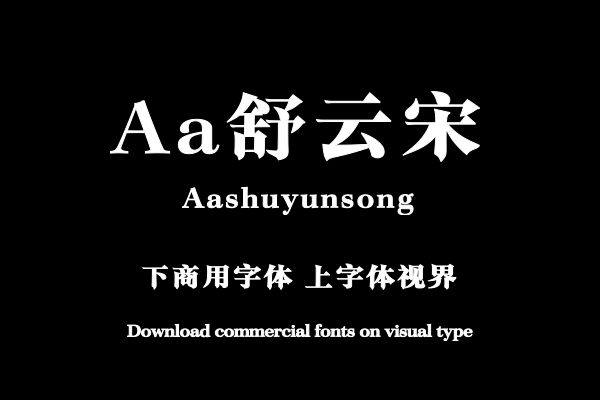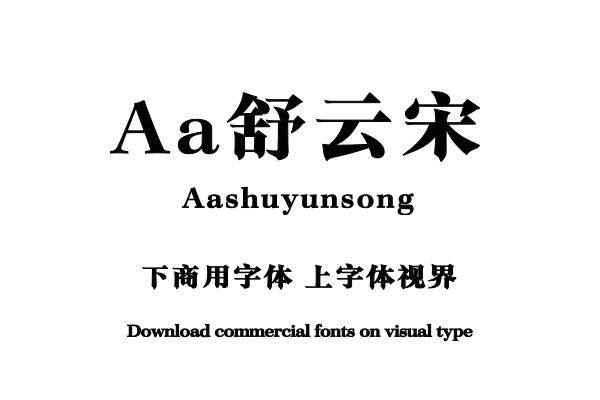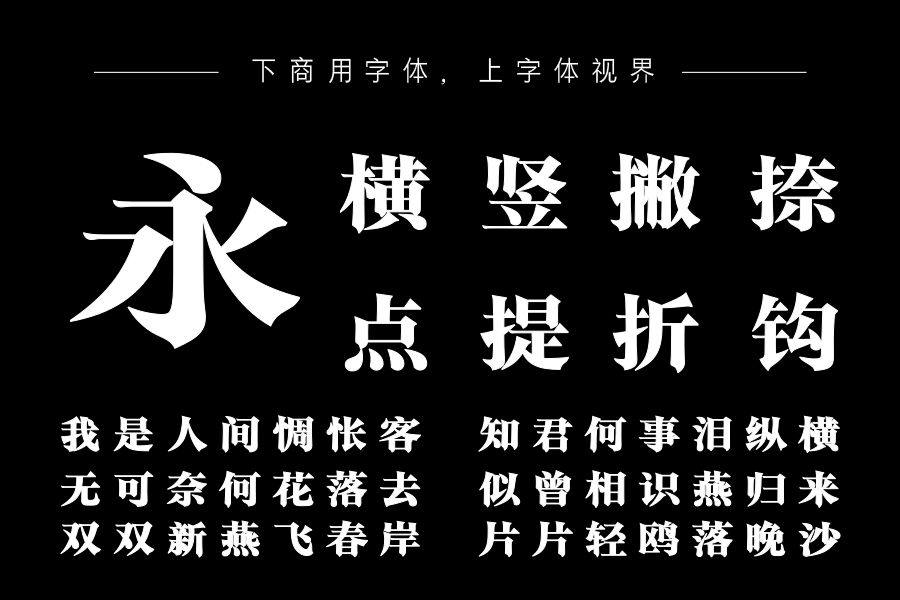
以竖和钩末端的衬角表现毛笔书写的提按和律动感,在宋体结构下凸显楷书风韵,衬角和强烈的粗细对比也形成了良好的装饰效果,使这套宋体作为标题大字号使用时细节更加丰富。购买须知:“下载服务费”与“字体VIP”所获得字体 仅用于个人非商用, 商用请联系付费授权。本字体为电脑用字,手机没有root权限不支持直接手机换字(手机如何root,请自行百度搜索教程)。购买前请先 了解清楚后再付款 ,字体为虚拟产品无法回收 一旦购买不支持退款。